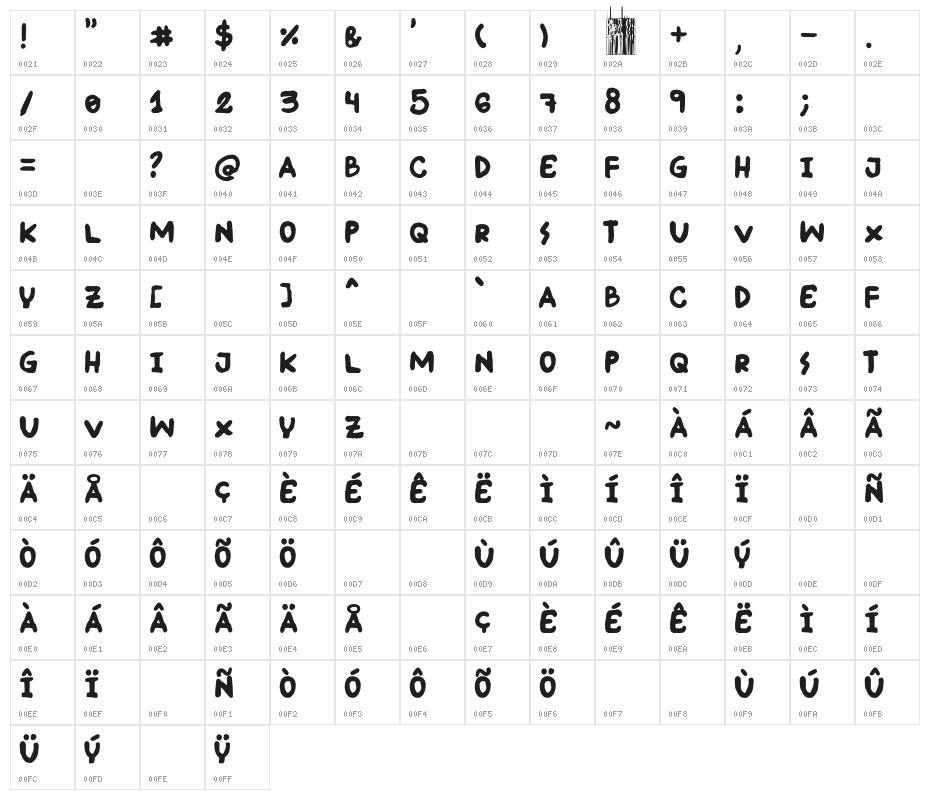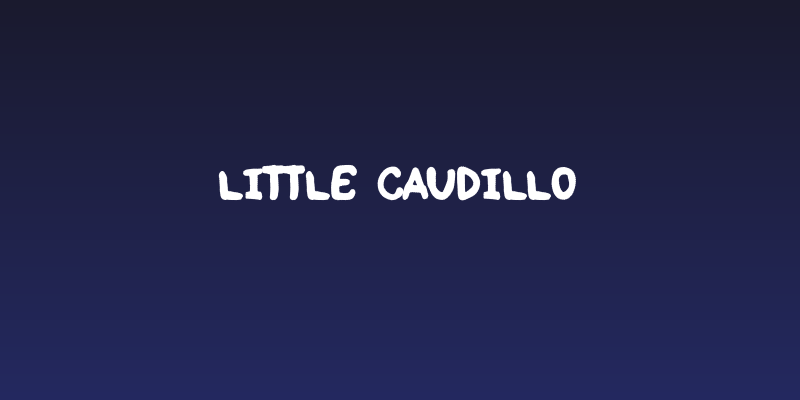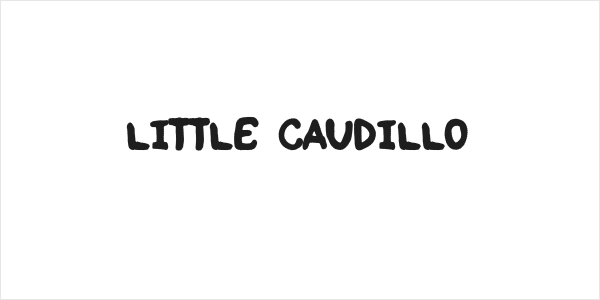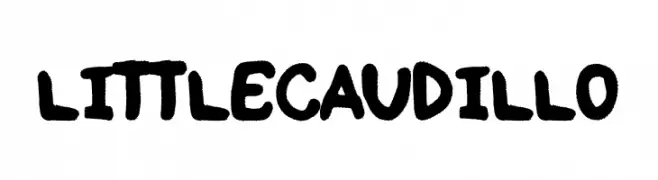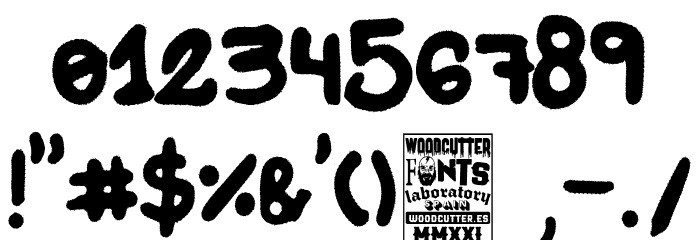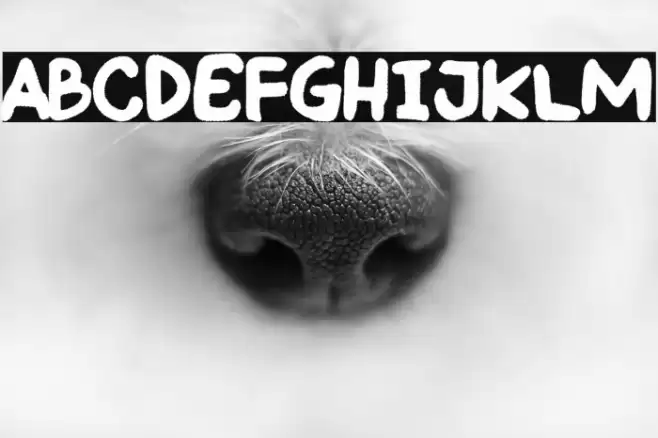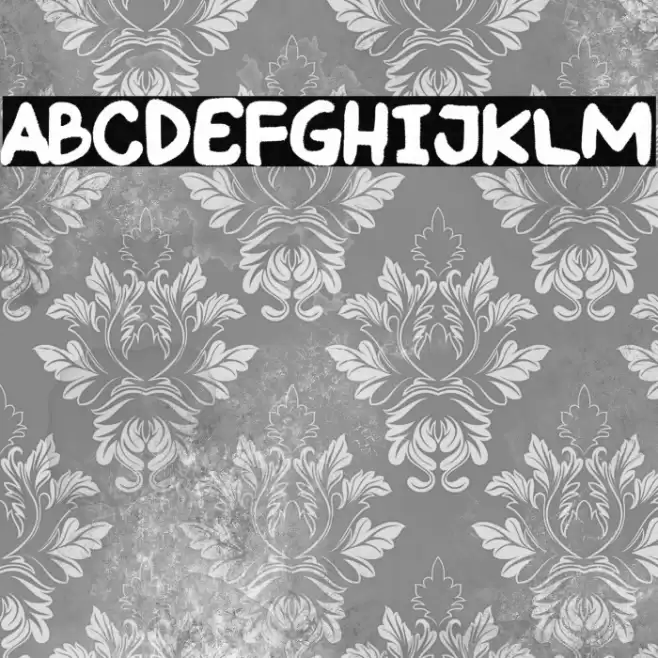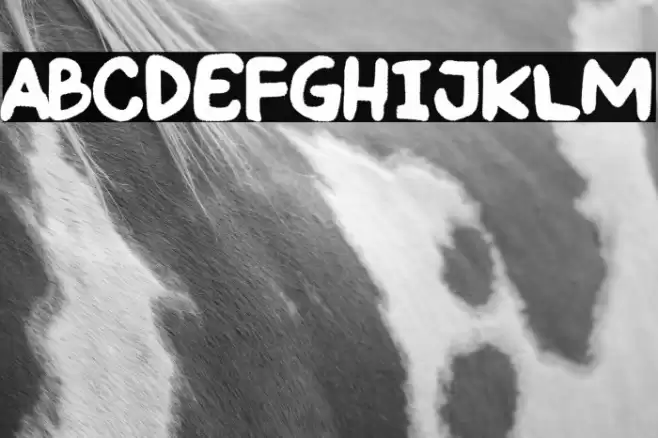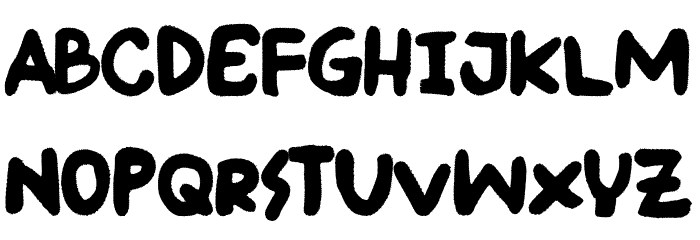
Little Caudillo Font
| Progetti proposti | Ideal for children's books, playful posters, creative branding, and informal invitations. |
Little Caudillo